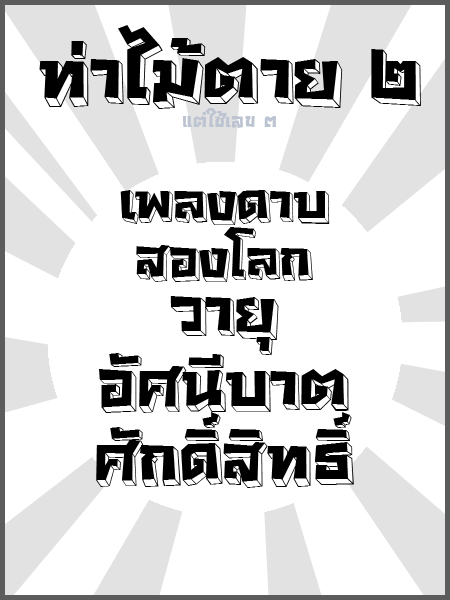
Layiji ท่าไม้ตาย ๒
ฟีเจอร์
1. มันคือตัว headline เท่านั้น ไม่ให้ใช้กับตัวเล็กๆ เพราะมันจะไม่เห็นรายละเอียด สรุปยิ่งใหญ่ยิ่งดี เหมาะกับงาน โปสเตอร์ billboard  มีปัญหามั้ยครับ 5โอ  :35:(ความจริงอิจฉาฟอนต์มัน ไว้จะทำแบบมาตรฐานบ้างนะจ๊ะ)
2. วรรณยุกต์ไม่ลอยด้วย Template ของทั่นนายพล
3. เช็คช่องไฟอย่างดี ไม่มีตัวอักษรทับซ้อน ด้วย ชุดอักษรของ bubbleball
ภาษาอังกฤษล่ะเลย์จิ?
แต่ฟ๐นต์แปลกดี เยี่ยม  :22:
เหมาะกับ headline จริง ๆ ด้วย
ท่าไม้ตาย ๒ แต่ใช้เลข ๓
สวยดีครับ ชอบตัว Z กับ ม ม้า  :42:
แล้วที่เฮียเคยบอกว่าจะเปลี่ยนสีตรงเงาได้ด้วยอะ?
ได้ แต่ยังไม่ได้ทำ  :02:
สวยจัง เก๋ไก๋  :12: น่าเอาไปใช้กับหนังสือการ์ตูน
สวยจัง ไว้จะขอเอาไปทำหน้าปกงานค่ะ  :25:
สวยมากครับ ดูหนักแน่น ฟาดทีเดียวตาย
หึหึหึ แนวทดลองได้มั้ยเนี่ย
แต่อยากให้ใช้สีขาวอ่ะ